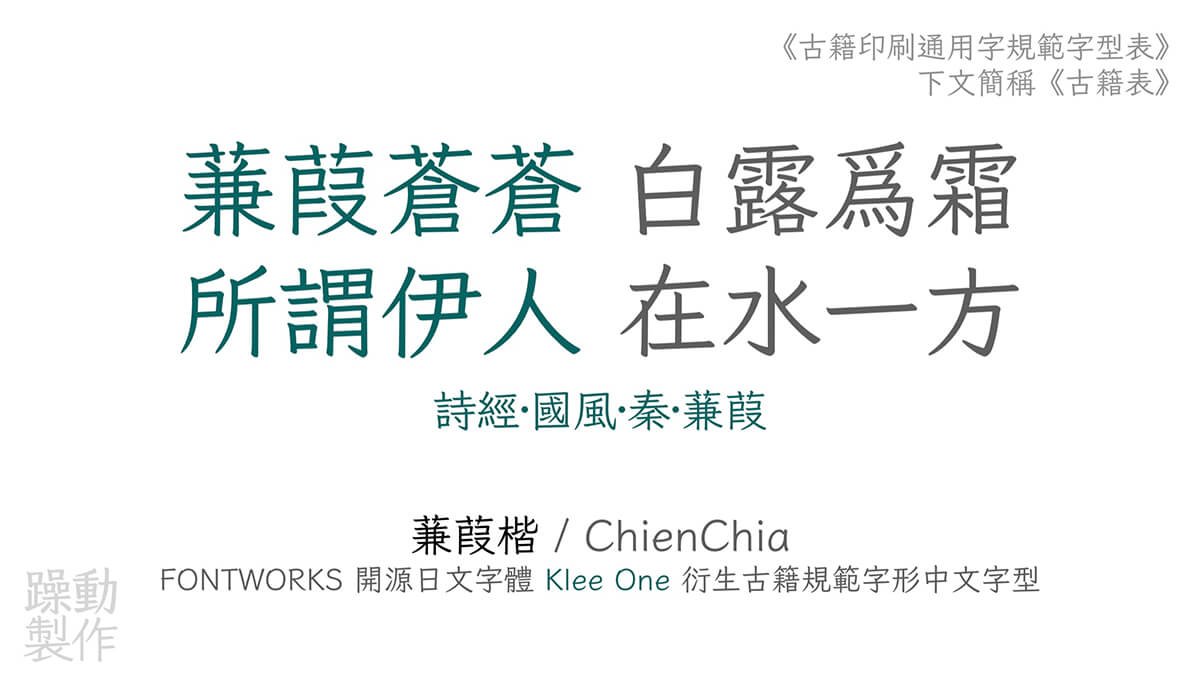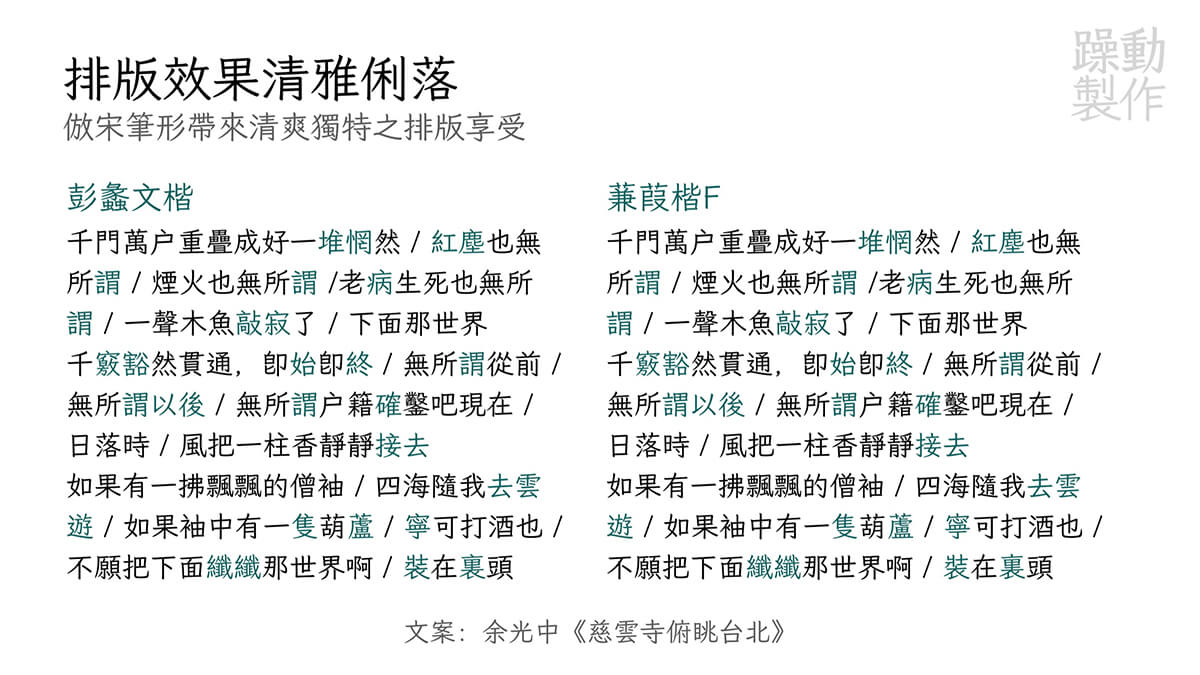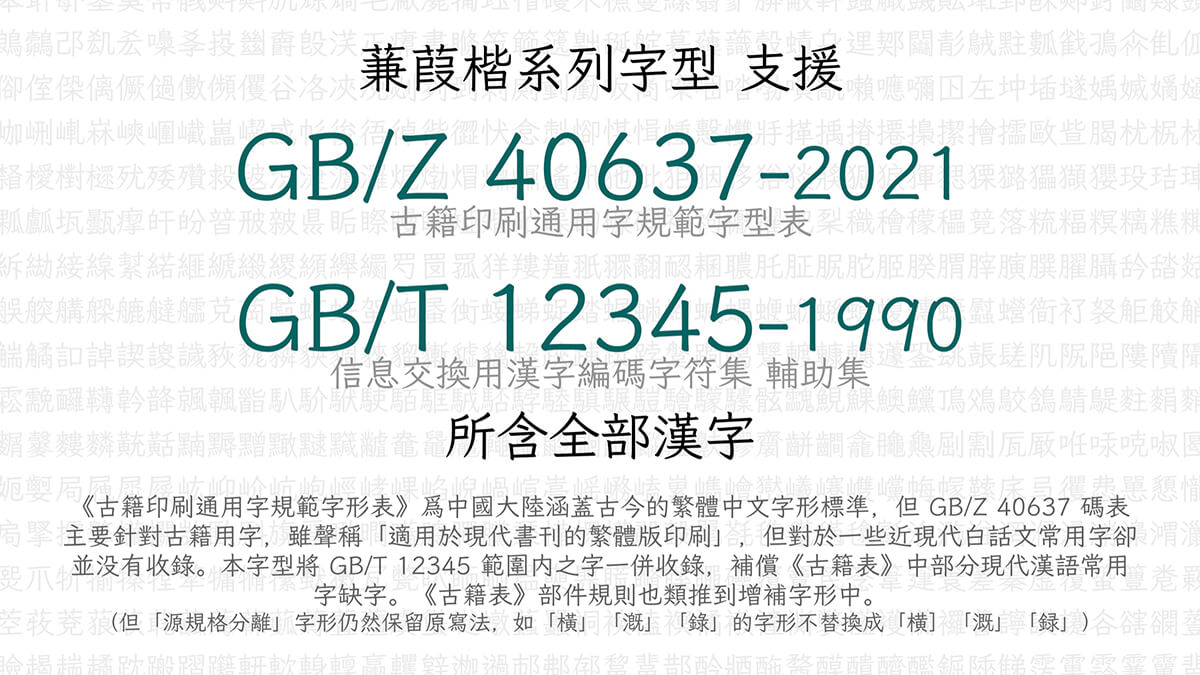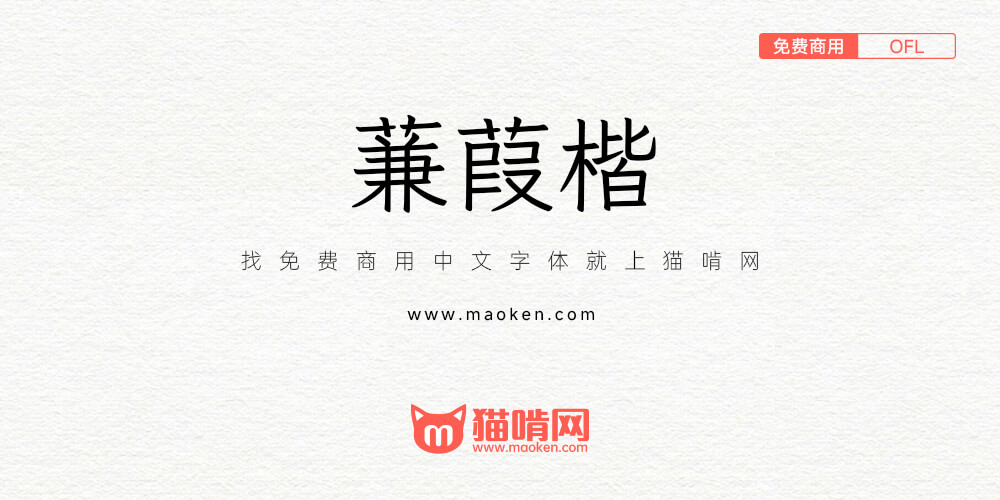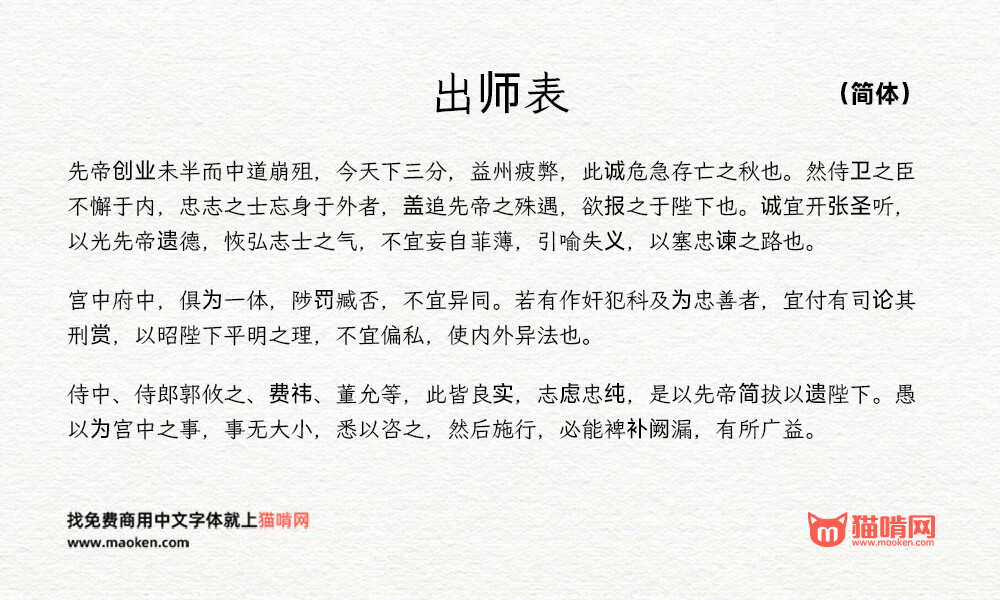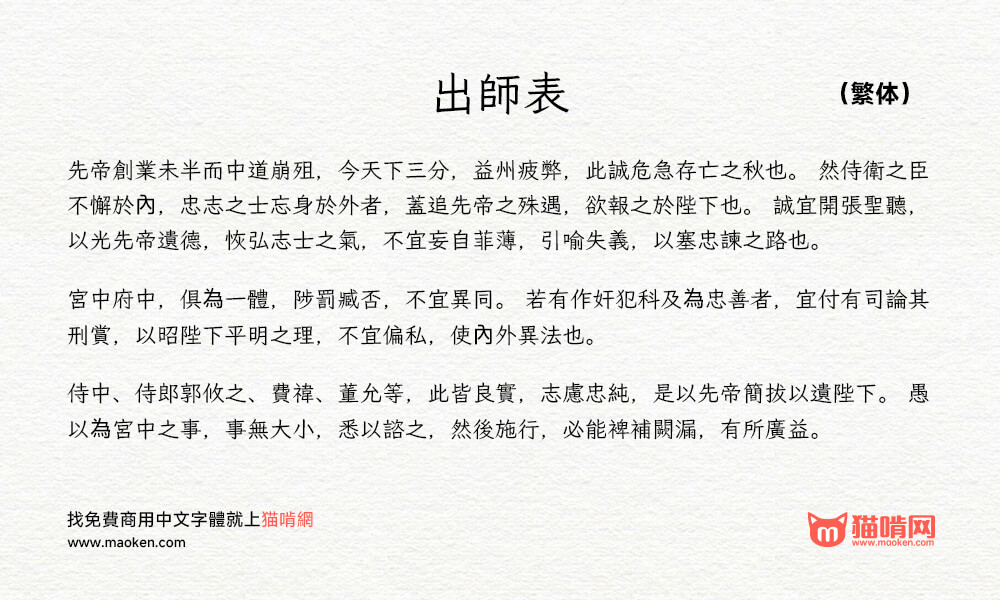
《蒹葭楷》是基于 Fontworks(现日本蒙纳株式会社,Monotype K.K.)所发布的开源字体 Klee One 的衍生字体,参考《古籍印刷通用字规范字形表》(GB/Z 40637-2021)收字和调整字形。
《古籍印刷通用字规范字形表》(GB/Z 40637-2021)是新中国成立以来第一次对传世古籍印刷字的第一次整理规范,也是中国大陆第一部正式针对繁体字制定的字形规范。这部指导性技术文件声称「适用于传世古籍的印刷出版,以及现代书刊的繁体版印刷」,共收录了 14,250 个汉字字形,并提供每个字的首音和 ISO/IEC 10646 编码。其收录 GB/Z 40637-2021 范围
字汇
- GB/Z 40637-2021 所收录的 14,250 个汉字,用于「传世古籍」所需汉字的排版与显示;
- GB/T 12345-1990 所收录的 6,866 个汉字,用于「现代书刊的繁体版本」所需汉字的排版与显示;
- Unicode 康熙部首区段所收录的 214 个部首字符,参考《康熙字典》总目中的部首字形进行取舍调整;
- 全半角 ASCII、拉丁补充-1 区、拉丁扩展 A 区、拉丁扩展 B 区、国际音标扩展区、拉丁附加扩展区、注音符号;
- 现代标点符号,以及古代汉语勾乙号「𖿢」、重文号「𖿣」;
- 易经、太玄经、算筹、中国象棋、中国传统圆形吉祥图案等符号;